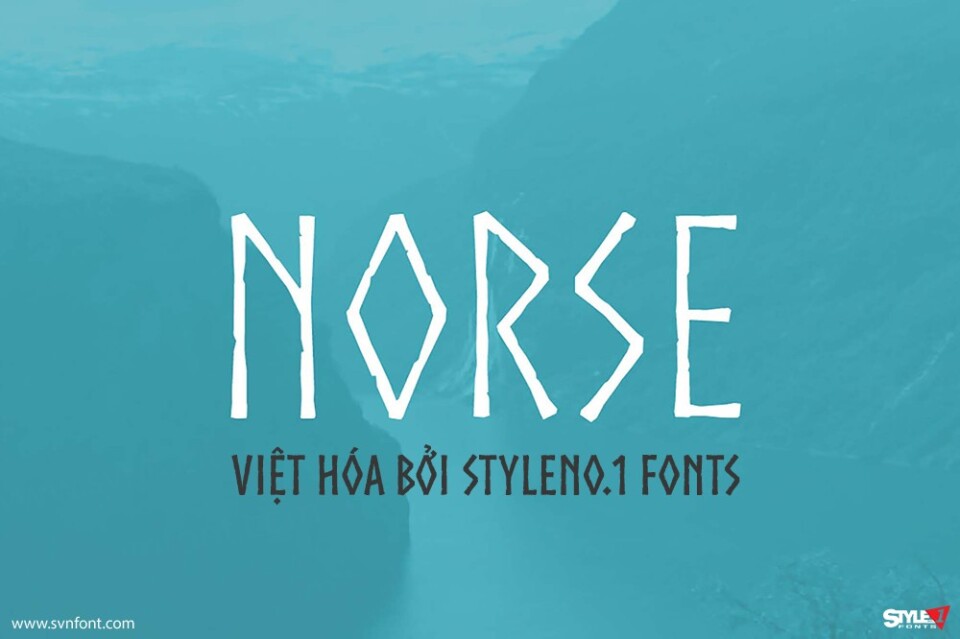
Font việt hóa SVN Norse (2 fonts)
Giới thiệu bộ Font việt hóa SVN Norse (2 fonts) độc đáo
Trong thế giới sáng tạo, việc lựa chọn một Font Miễn Phí phù hợp là yếu tố then chốt để tạo nên hồn cốt cho tác phẩm. Font việt hóa SVN Norse (2 fonts) là bộ phông chữ được lấy cảm hứng mạnh mẽ từ bảng chữ cái Runes cổ đại của vùng Scandinavia. Với những đường nét góc cạnh, mạnh mẽ và mang đậm hơi thở của các chiến binh Viking, bộ font này đã trở thành lựa chọn hàng đầu cho các dự án mang phong cách thần thoại, lịch sử hoặc kỳ bí.
Đặc điểm nổi bật của Font việt hóa SVN Norse (2 fonts)
Thiết kế đậm chất sử thi và phong trần
Bộ Font việt hóa SVN Norse (2 fonts) bao gồm hai biến thể là Norse Regular và Norse Bold. Mỗi biến thể đều giữ nguyên cấu trúc chữ thô mộc nhưng không kém phần tinh tế. Các ký tự được chăm chút tỉ mỉ để đảm bảo tính thẩm mỹ cao khi ứng dụng vào bìa sách, poster phim hành động hay logo thương hiệu. Sự kết hợp giữa nét thẳng dứt khoát và các góc nhọn đặc trưng giúp thiết kế của bạn nổi bật hơn bao giờ hết.
Khả năng hiển thị và tính tương thích cao
Dù mang phong cách cổ điển, Font việt hóa SVN Norse (2 fonts) vẫn đảm bảo khả năng đọc tốt trên cả phương tiện in ấn và kỹ thuật số. Font đã được tối ưu hóa tiếng Việt hoàn chỉnh, không lỗi dấu, giúp các nhà thiết kế tại Việt Nam dễ dàng truyền tải thông điệp mà không gặp bất kỳ trở ngại nào về kỹ thuật.
Kết luận và trải nghiệm Font việt hóa SVN Norse (2 fonts)